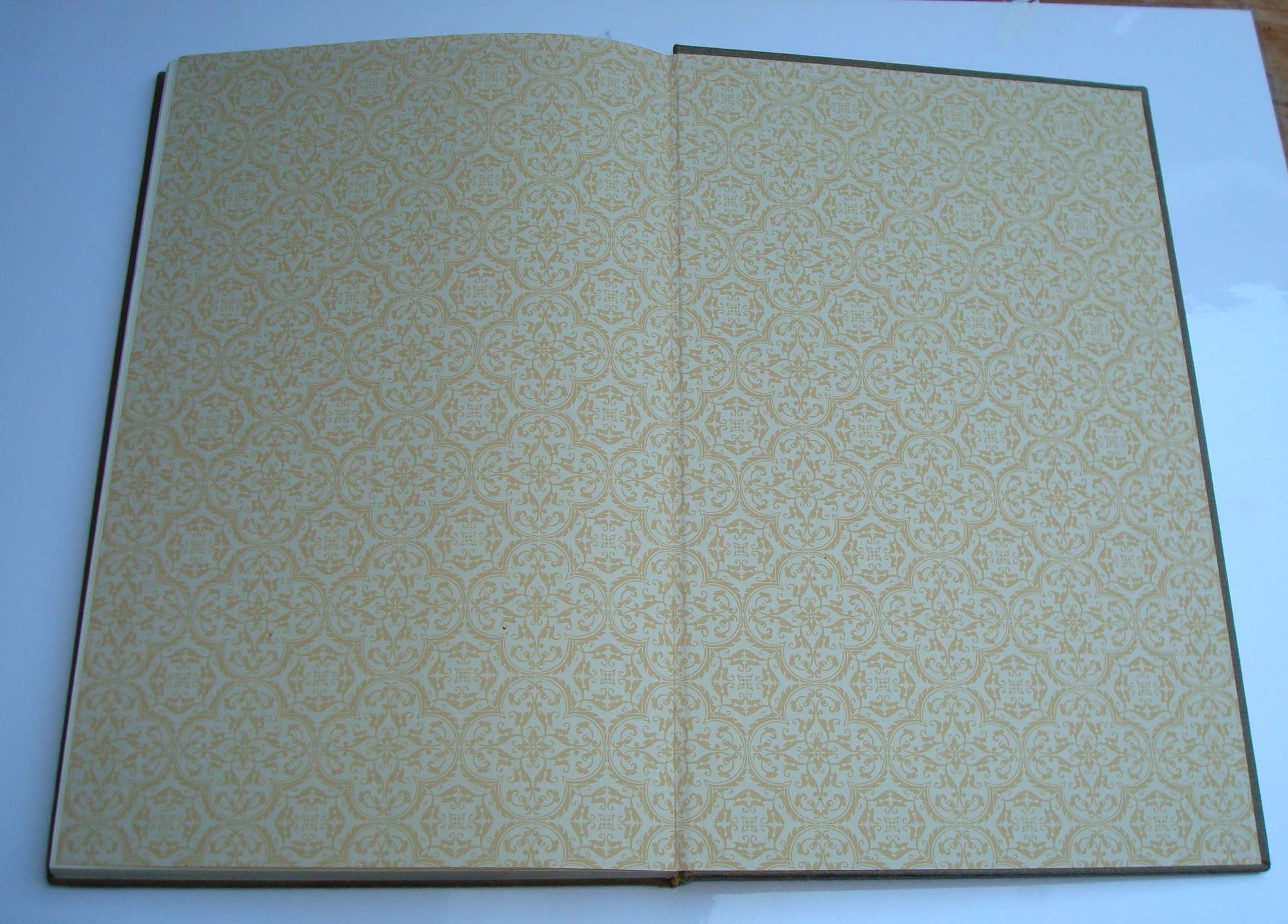
Envoyez-donc une jolie photo !
C' est le cas du livre que je veux décrire; pour lequel d'ailleurs cette feuille n'est pas marbrée mais composée avec des ornements(ou vignettes, fleurons, etc.).
La voici !